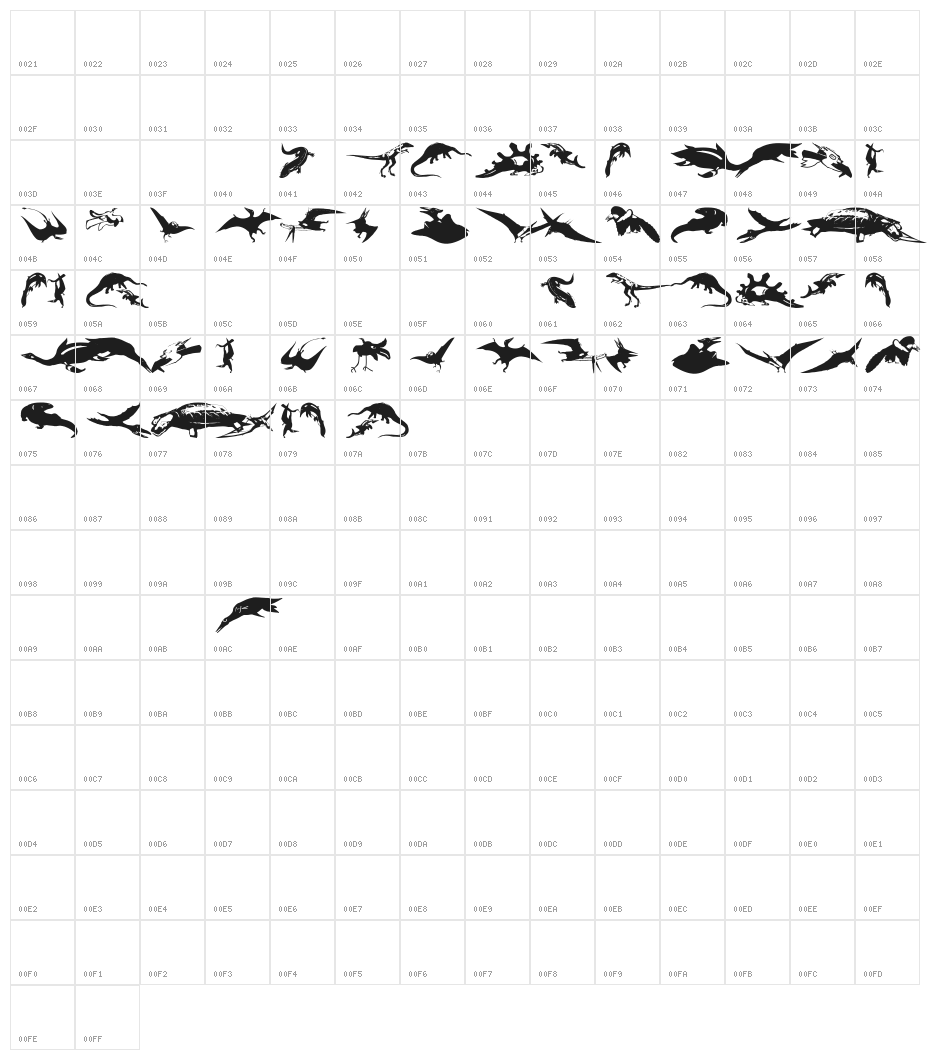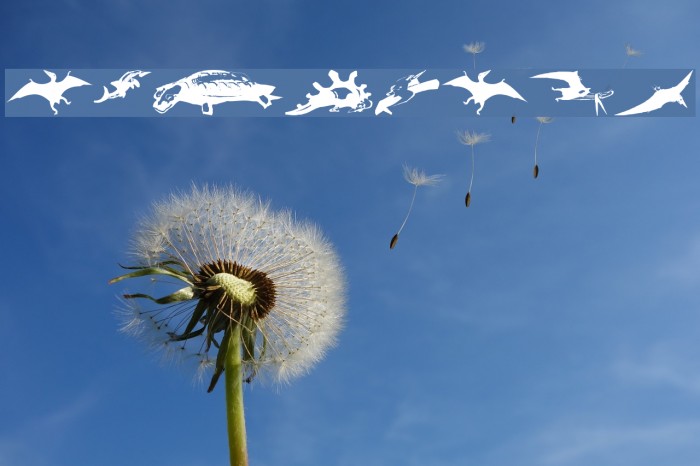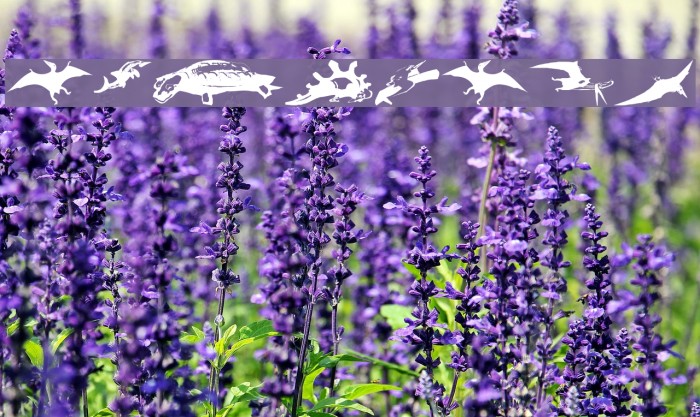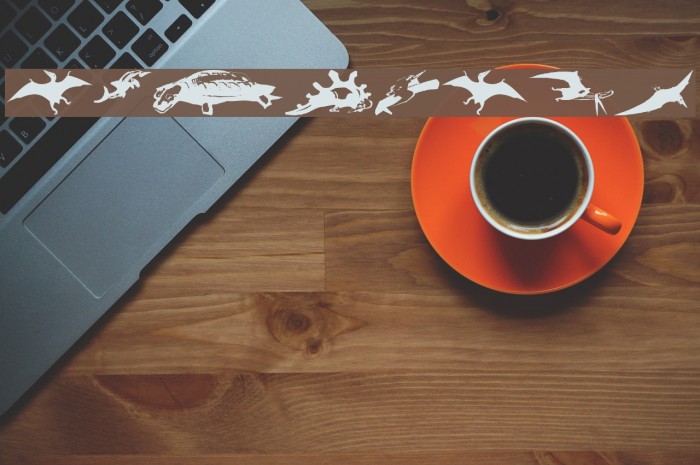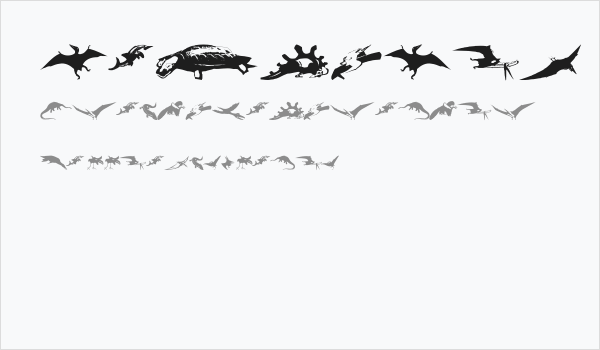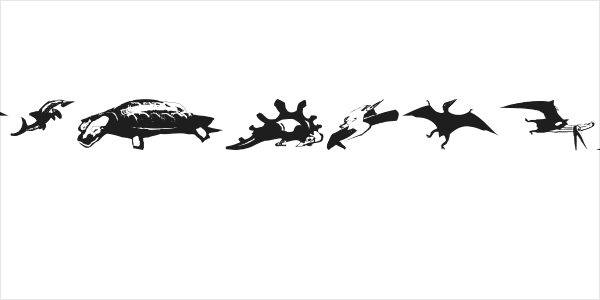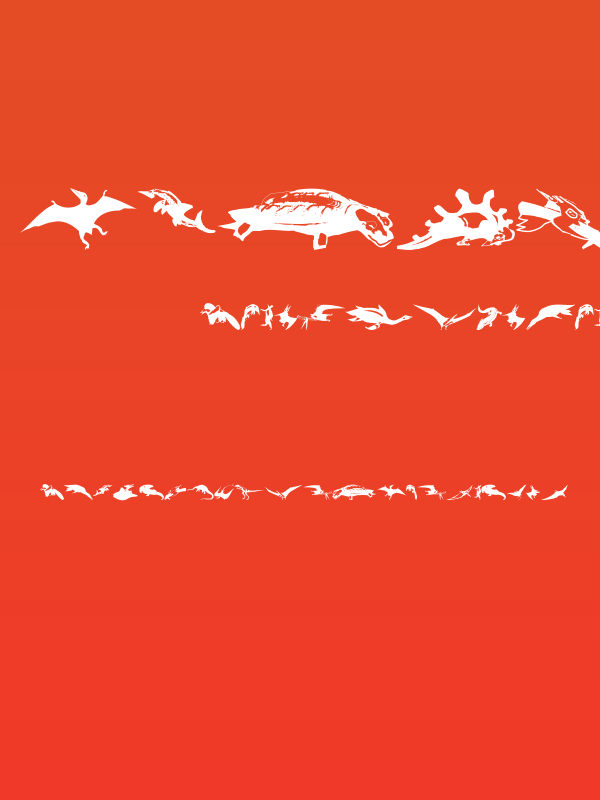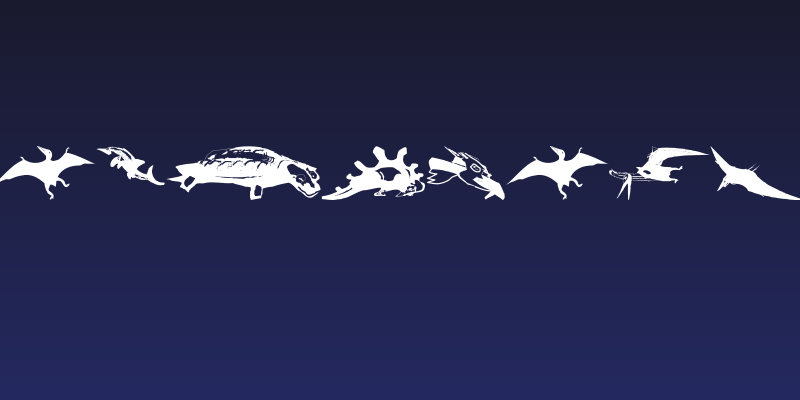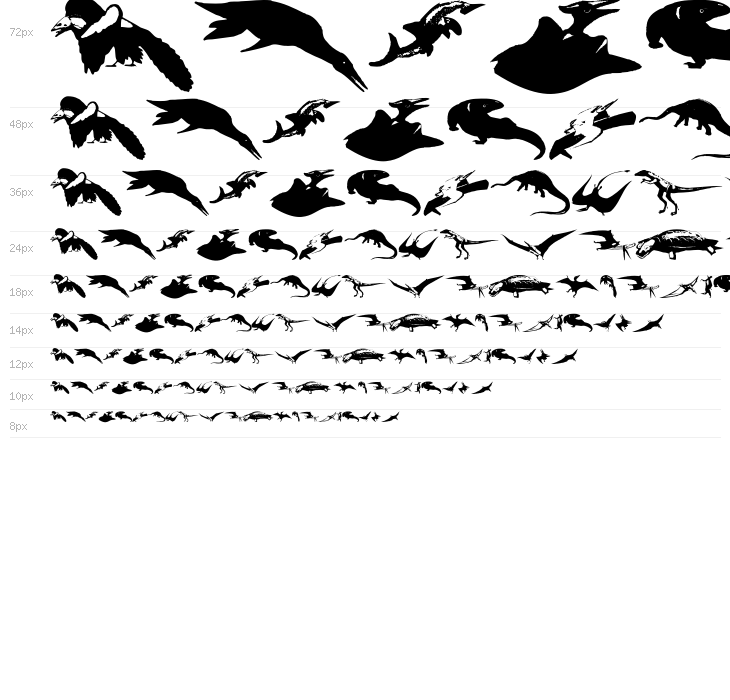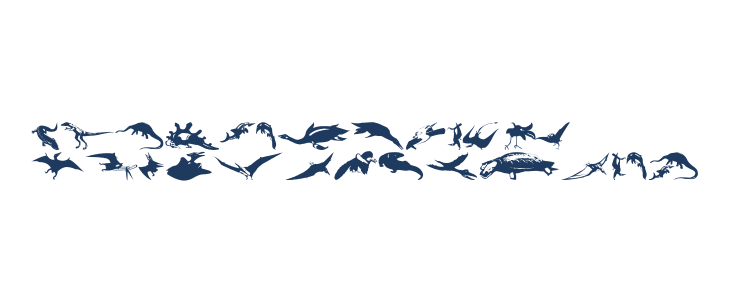
NewDinos Font
| Stile generale | Decorative, Playful, Thematic |
| Caso d'uso | Headlines, Logos, Posters, Themed graphics |
| Progetti proposti | Children’s books, educational posters, themed party invitations, museum exhibits, playful branding. |